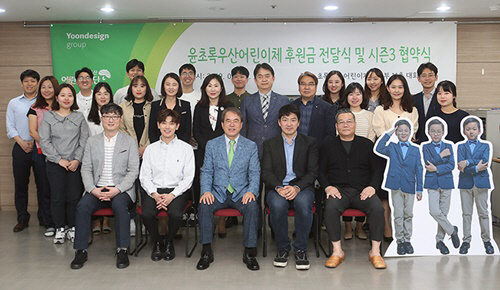
㈜윤디자인X에릭남X초록우산 어린이재단, '한글희망나무' 캠페인 진행
지난 24일 초록우산어린이재단에서는 ㈜윤디자인그룹의 윤초록우산어린이체 후원금 전달식 및 시즌3 협약식이 열렸다.
㈜윤디자인그룹은 글꼴디자인 회사로 ‘한글로 희망을 전합니다!’라는 슬로건 아래 사회적 책임을 다하고 한글 디자인의 가치를 널리 알리기 위해 10년 전 ‘희망한글나무’ 캠페인을 시작했다.
올해 벌써 열한번째로 이번에 개발된 ‘윤초록우산어린이체’는 세계 어린이날을 맞아 아동복지기관 초록우산어린이재단과 함께 공동으로 기획했다.
서체를 개발해 후원 모금을 통해 제공하고 모금액을 다시 소외 아동에게 기부하는 나눔 프로젝트로 가수 에릭남과 ㈜윤디자인그룹의 재능 기부로 진행됐다.
에릭남의 손글씨를 윤디자인그룹 디자이너들이 디지털화하여 ‘윤초록어린이체’를 완성하였는데 디자이너에 따르면 “어린이가 또박또박 집중해서 쓴 것처럼 반듯한 인상을 표현했고 끝맺음을 둥글게 처리하여 귀여운 느낌으로 제작했다”고 말한다. 서체는 글씨를 쓴 사람과 개발한 사람의 따뜻한 마음씨가 담겨 밝고 긍정적인 에너지를 전달한다.
‘윤초록우산어린이체’가 조금 더 특별한 이유는 한국어와 영어를 비롯해 일본어, 스페인어, 포르투갈어, 독일어, 이태리어, 네덜란드어 등 북미와 유럽 지역의 다양한 언어 사용이 가능해 세계 어린이 및 후원자들과 소통할 수 있다는 점이다. 지난 2월에 시작해 4월말까지 소중한 마음이 더해져 모인 후원금은 각종 위험과 범죄, 식량 부족 등 열악한 환경에 노출된 아프리카 슬럼지역 아동을 지원하는 데 사용된다.
한편 ㈜윤디자인그룹은 이날 자리에서 배우 송일국의 세 쌍둥이(대한, 민국, 만세)와 함께 한글로 희망을 전하는 다음 프로젝트를 예고하였다.
㈜윤디자인그룹 편석훈 대표는 “희망한글나무가 무럭무럭 자라나 아이들이 밝은 미래를 꿈꾸고 성장하는 데 도움이 될 수 있도록 더 많은 사람들이 공감하고 참여하는 뜻깊은 캠페인이 되길 바란다”는 말을 전했다.